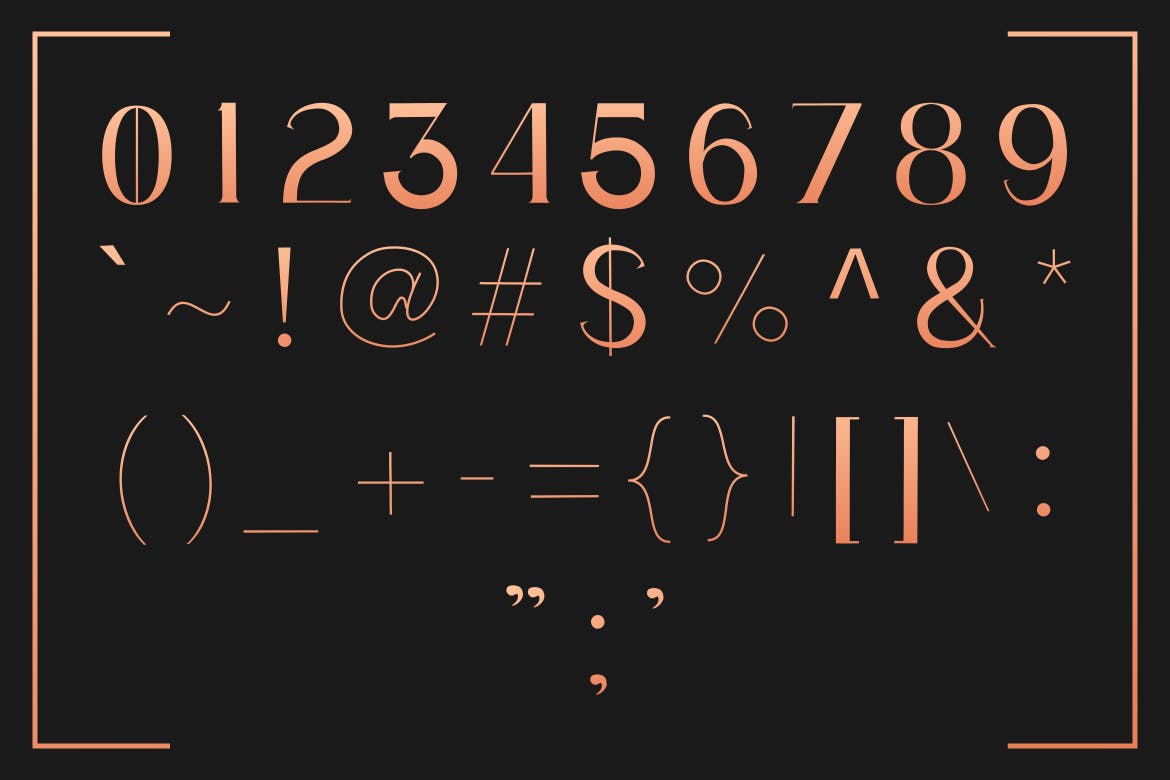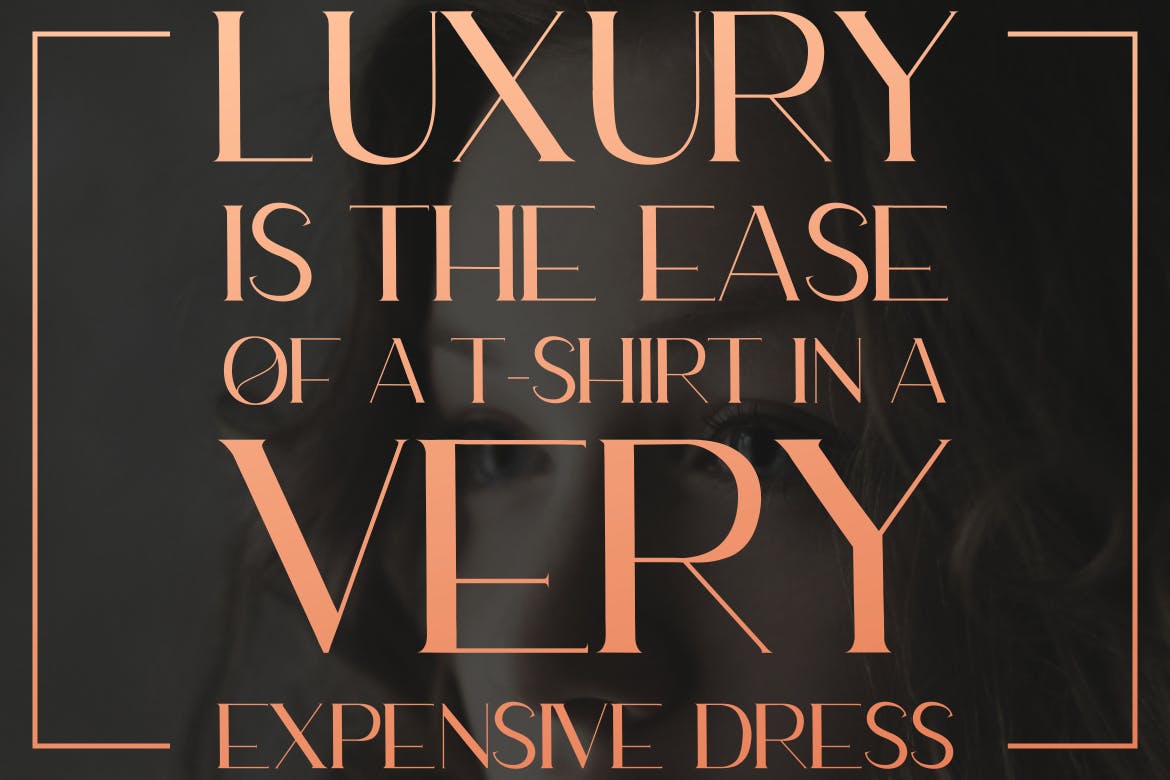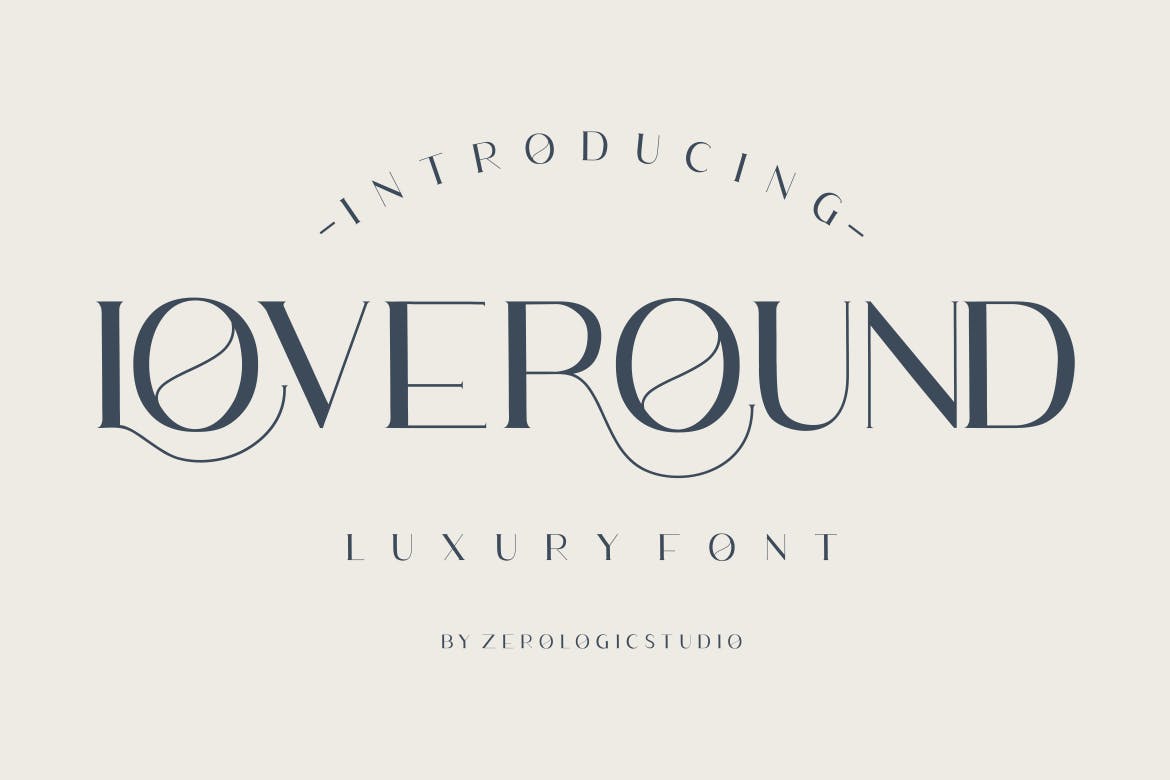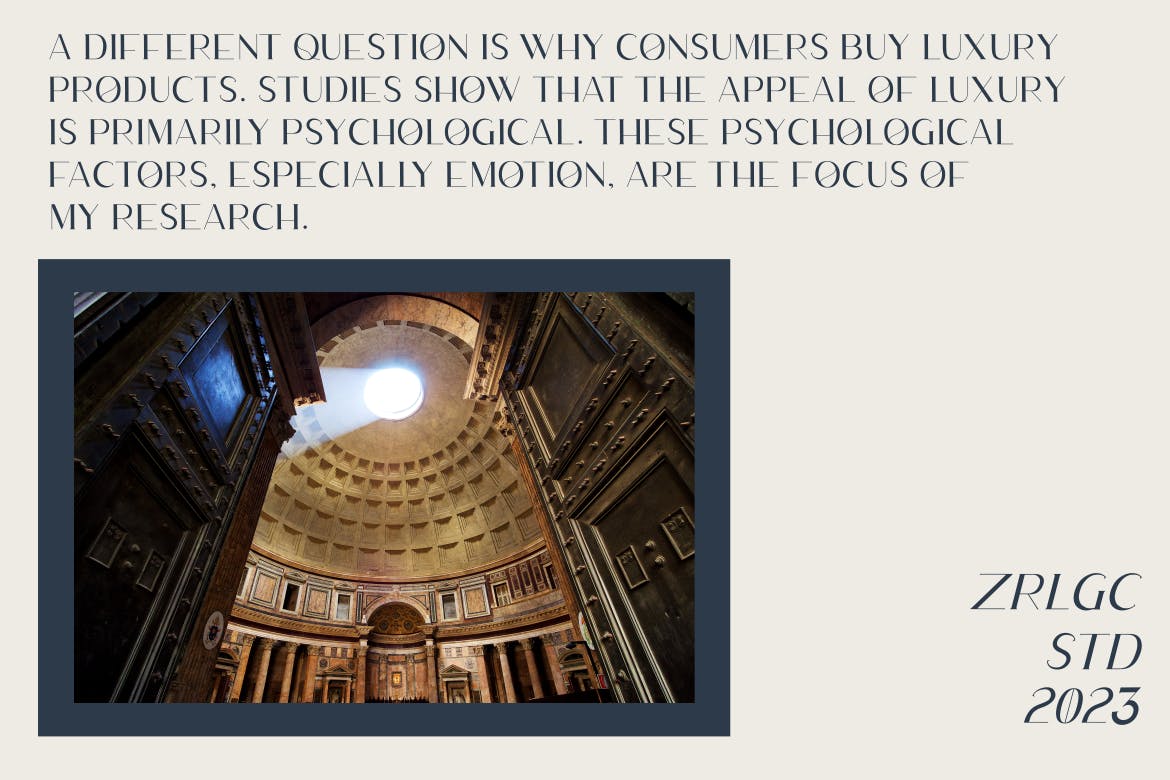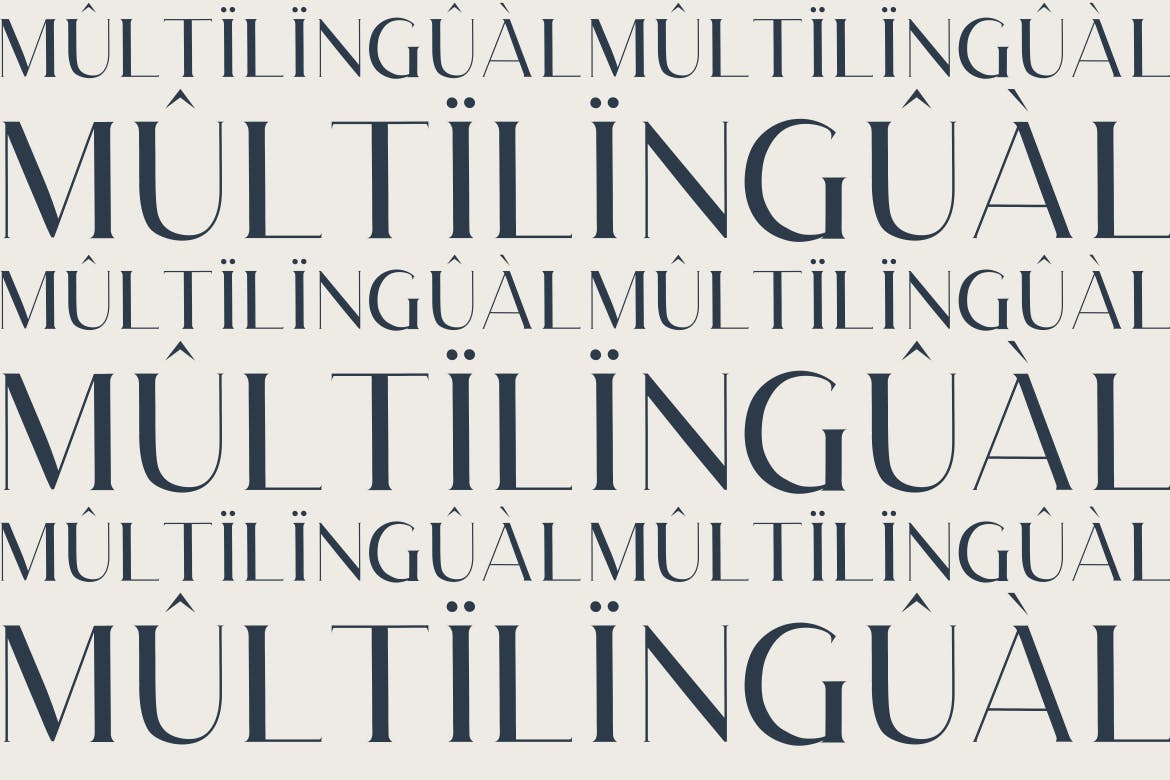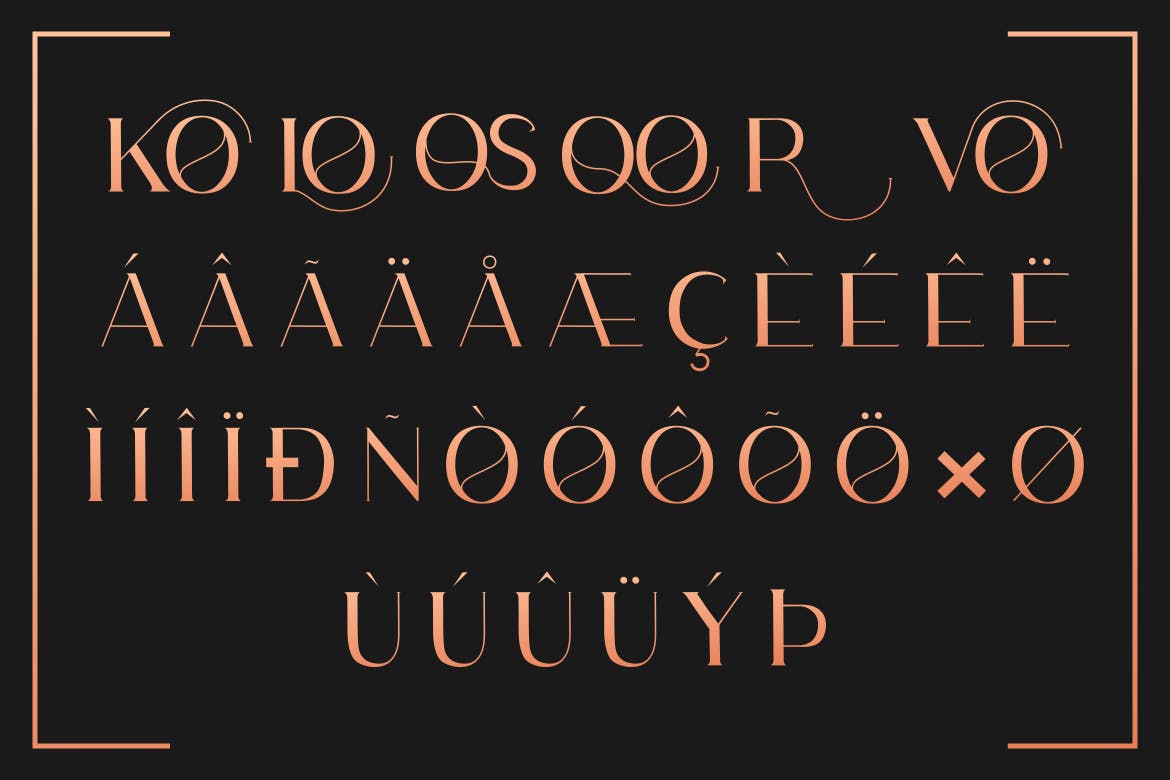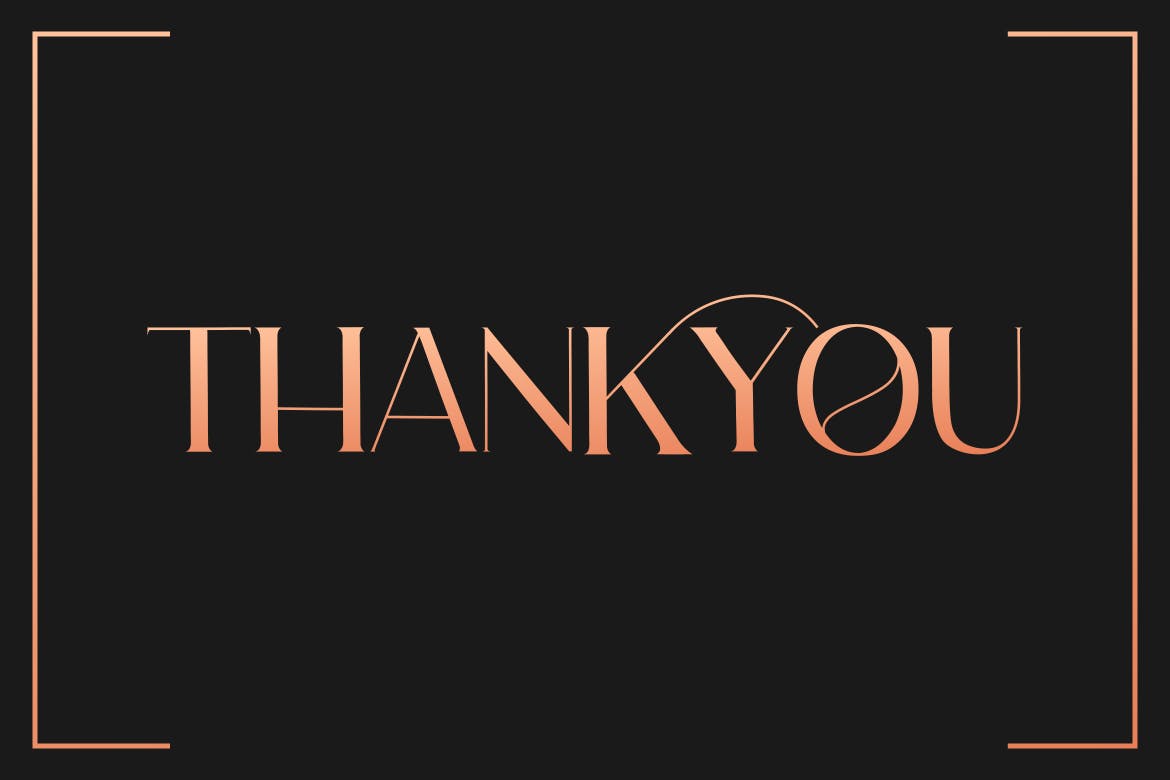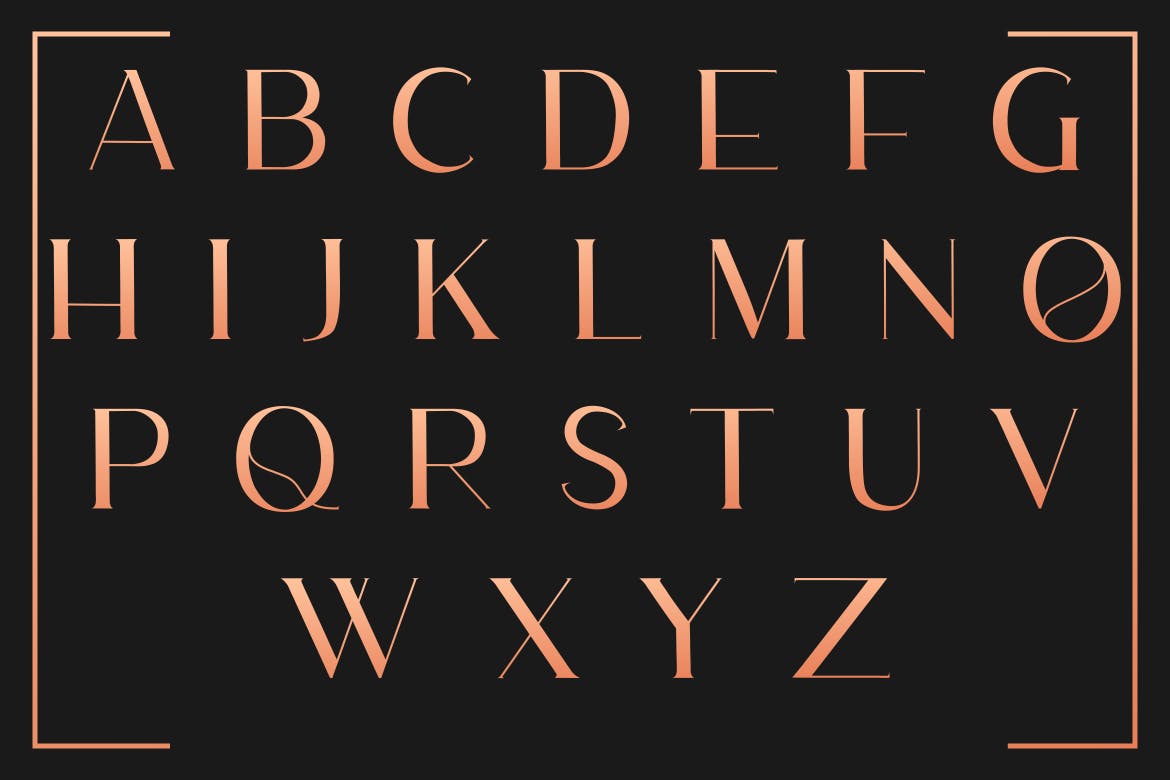
فونت لاوراند یک فونت سریف مدرن و لوکس است که با طراحی خاص خود برای نیازهای شما ایجاد شده است. این فونت جذاب شامل حروف بزرگ، کوچک، اعداد و نمادها است. فونت قوی و تند این امکان را به شما میدهد که برای عناوین، تایپوگرافی، پوسترها، مجلات، بروشورها، بستهبندیها، وبسایتها و بسیاری از پروژههای طراحی دیگر از آن استفاده کنید و طراحیهای خود را به شکلی خلاقانه و جذاب ارائه دهید.